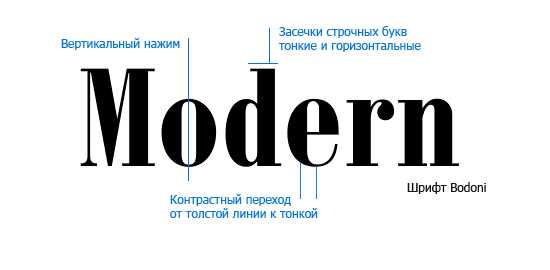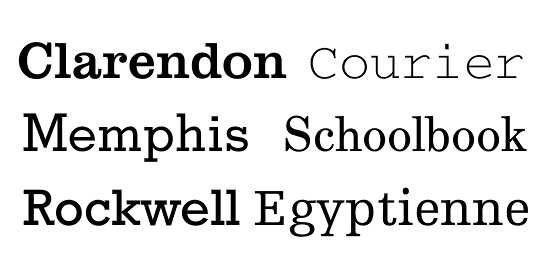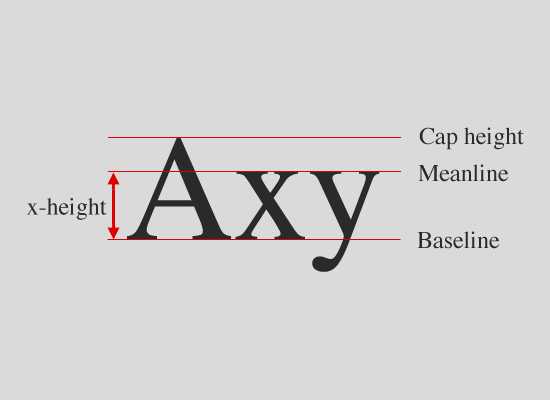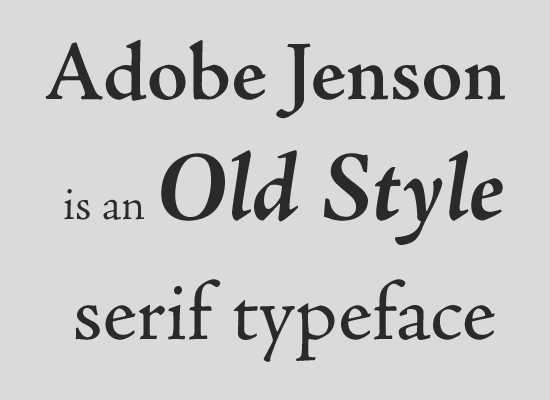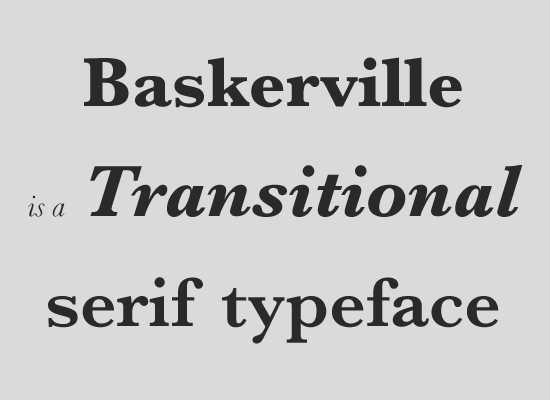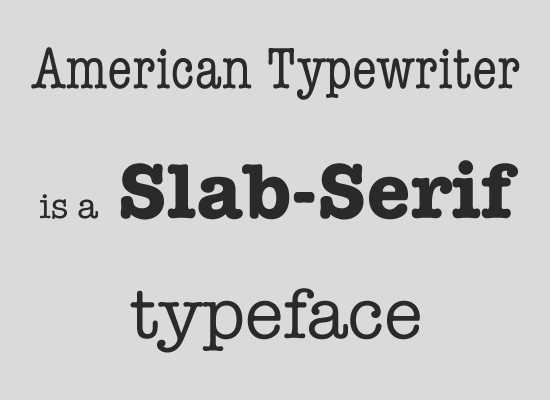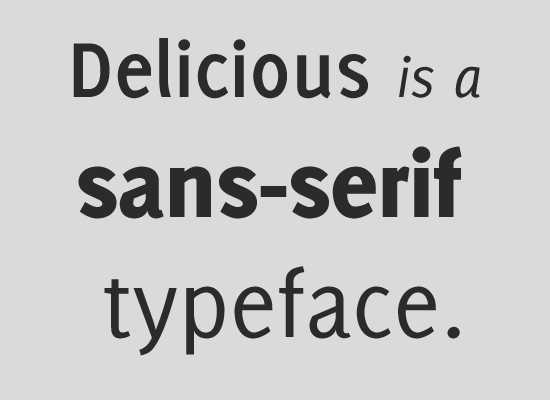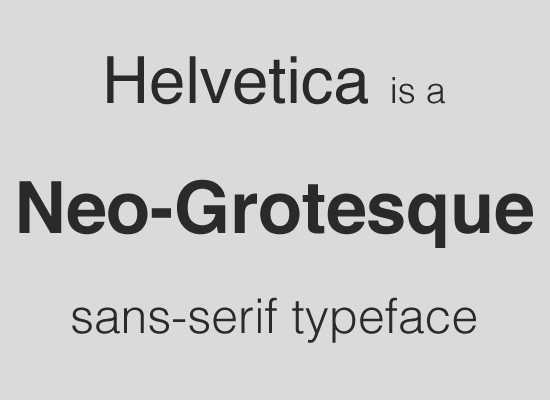
Сегодняшняя статья является частью материала бесплатного e-mail курса по основам графического дизайна (доступ к которому в ближайшее время будет открыт) из раздела типографики. Знания, которые даются в ней, обязательны для изучения. Вначале может показаться, что пара новых слов-терминов мало на что может повлиять, но это в корне не так.
Знания о классификации шрифтов, их особенностях, эпохе создания и т.д. очень полезны (и даже незаменимы), когда речь идет о сочетании различных шрифтов в одной работе. Существует достаточно много вариантов разделения шрифтов по группам, но чтобы составить более менее общее представление, достаточно запомнить два основных.
Наиболее известная классификация шрифтов — по их анатомии:
С засечками (Антиквы, Serif)
На каждой букве в таких шрифтах присутствуют засечки (думаю, объяснять, что это такое, не стоит), что и стало основой бесхитростного названия данной группы. Они часто используются для сплошного текста в верстке печатных изданий; для набора подобного текста в web антиквы были признаны трудночитаемыми и уступили место гротескам. Антиквы отлично подходят для заголовков.
Шрифты с засечками бывают:
- Старого стиля (Old Style)
По названию нетрудно догадаться, что это одни из первых шрифтов. Их также называют гуманистической антиквой, истоки которой уходят в далекий XV век. Эти шрифты каллиграфичны и разрабатывались как имитация рукописного текста того времени. Основным их признаком является ярко выраженный наклон оси овалов, малая контрастность (разница в толщине основных и дополнительных штрихов), наклоненная ось строчной «е» и характерная капелька строчной «а». Высота строчных букв достаточно маленькая.Примеры гуманистической антиквы: Centaur, Adobe Jenson, Goudy Old Style, Guardi, Arno. - Гаральды (Old Style)
Иначе их еще называют итало-французской антиквой старого стиля или Альдине. Начало развития этих шрифтов датируется примерно концом XV века. Контраст их символов выражен немного больше, наклон оси овала становится меньше и приближается к перпендикуляру. Ось строчной «е» параллельна базовой линии шрифта. Засечки — изящнее, буквы — пропорциональнее, а высота строчных букв — больше. Достаточно часто Гаральды не выделяют в отдельную группу, либо причисляют к переходной антикве.Представители этого типа шрифтов: Bembo, Dante, Adobe Garamond, Stempel Garamond, Granjon, Poliphilus, Caslon, Sabon, Palatino, Galliard. - Переходного стиля (Transitional Serif)
Название говорит нам о шрифтах, которые являлись ступенью при переходе от антиквы старого стиля к новому стилю. Этот переход начался примерно в конце XVII века. Особенностью этого стиля является усиление контраста основных и дополнительных штрихов. Оси овалов становятся вертикальными или имеющими незначительный наклон, а засечки плавными.Таких шрифтов не так уж и много, наиболее известны Baskerville, Joanna, Melior, Clearface. Иногда в эту группу зачисляют гарнитуру Caslon, так как в этих шрифтах можно проследить признаки переходной антиквы, но обычно ее относят к антиквам старого стиля. - Нового стиля (Modern Serif)
В середине XVIII века тенденция, характерная для переходной антиквы, нашла свое логическое завершение в лице новой антиквы. Как вы могли заметить, этому «новому» стилю уже более 250 лет, но такое название к этому виду антиквы прилипло довольно прочно.Контраст между основными и дополнительными штрихами (а также засечками) достигает в них своего апогея, иначе говоря становится «толщиной с волос» или hairline. Силуэт букв четкий и официальный. Антиква нового стиля очень хорошо подходит для заголовков и считается акцидентной (что это означает читайте далее). Следовательно не рекомендуется использовать ее для набора больших блоков текста.Самые яркие представители этого типа — Bodoni и Didot. Также сюда относятся Basilia, Aviano, Walbaum, Ambroise и Scotch Roman.
- Брусковые (Slab Serif, Египетские)
Этот тип шрифта отличить очень легко по необычной форме его засечек — они прямоугольные. Контраст выражен незначительно. Как обычно, существуют некоторые исключения из этого правила, в некоторых классификациях их считают отдельным типом антикв. Например, гарнитура Clarendon, которая выглядит более «легкой» за счет повышенного контраста и немного скругленных засечек.Примеры: Baltica, Bruskovaya, Grenader, Xenia.
Без засечек (Гротески, Sans Serif, Рубленные)
Время рождения гротесков — начало XIX века. Как снова нетрудно догадаться их основной отличительной особенностью является полное отсутствие засечек. Они подразделяются на геометрические (основываются на правильных фигурах, и толщина штрихов не изменяется, например, Helvetica) и гуманистические (имеют небольшой контраст между штрихами и более каллиграфичны по сравнению с геометрическими, например, Optima).
Гротески — это простота и практичность. К ним относят Helvetica, Arial, Futura, Century Gothic, Gill Sans и др. Как говорилось ранее, такие шрифты отлично подходят для написания сплошного текста, особенно для web-страниц.
Рукописные
Первые подобные шрифты были разработаны в VXII-XVIII веках. Некоторые из них основывались на почерке известных мастеров. Такие шрифты очень элегантны. Они не подходят для набора сплошного текста, но замечательно смотрятся в заголовках.
Второй распространенный вид классификации — по роли шрифта.
По этому критерию выделяют текстовые (или наборные), акцидентные (заголовочные, выделительные) и декоративные шрифты.
4. Декоративный шрифт
К этой категории относятся большинство шрифтов, не попадающих в остальные категории. Декоративных шрифтов очень много и их количество увеличивается день ото дня. Из-за своей яркой экстравагантности такие шрифты стоит применять дозировано и аккуратно. Это могут быть логотипы, заголовки, надписи. Примеры декоративных шрифтов представлены у меня на сайте.